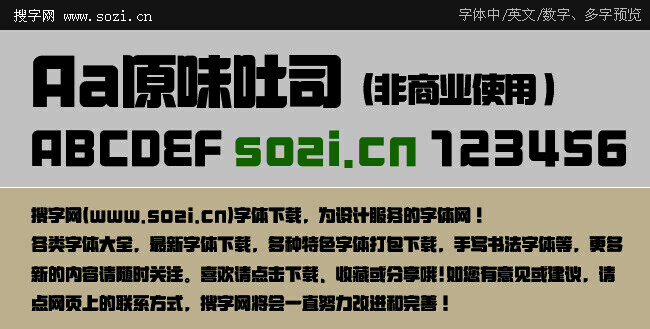
Aa原味吐司
搜字網(wǎng)給大家提供一款A(yù)a原味吐司(非商業(yè)使用)中文字體下載,該字體是一款中文藝術(shù)字體,字體粗壯醒目,字形剛勁有力,線條簡潔利落,視覺感非常好。適合圖書設(shè)計(jì)、卡通包裝、海報(bào)設(shè)計(jì)等應(yīng)用(此字體為個人非商用版,商用可以聯(lián)系QQ:1006760504)。
- 風(fēng)格類別: 海報(bào)POP體